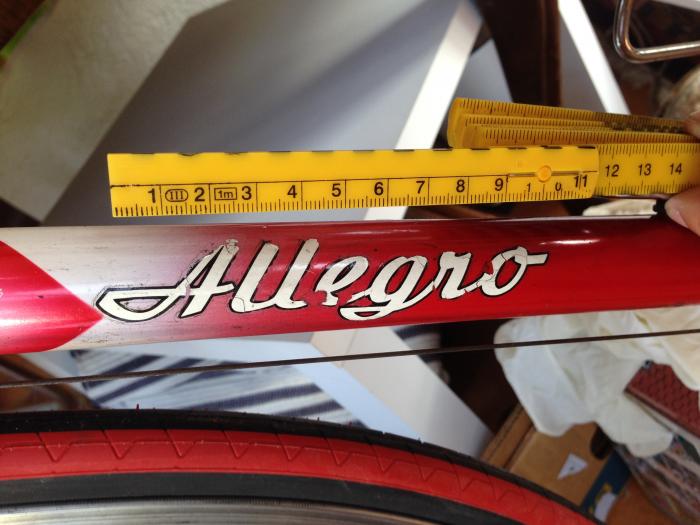
Allegro Handmade Schweizer Rennfahrad
Ich suche die Schriftart von dem angehäntem Bild.
Leider hat Allegro keinen einheitlichen Schriftzug für ihren Namen auf den Fahrrädern benutzt, was die Suche nach der Schrift schwieriger macht. Dieses Model gehört zu der "handmade" Serie.
Das Rennrad ist wahrscheinlich aus den Jahren 1960-1980, Allegro ist eine schweizer Marke.
Eine ähnliche Schrift ist aka Dora wobei deutliche Unterschiede (vorallem bei dem Grossen A) zu sehen sind.